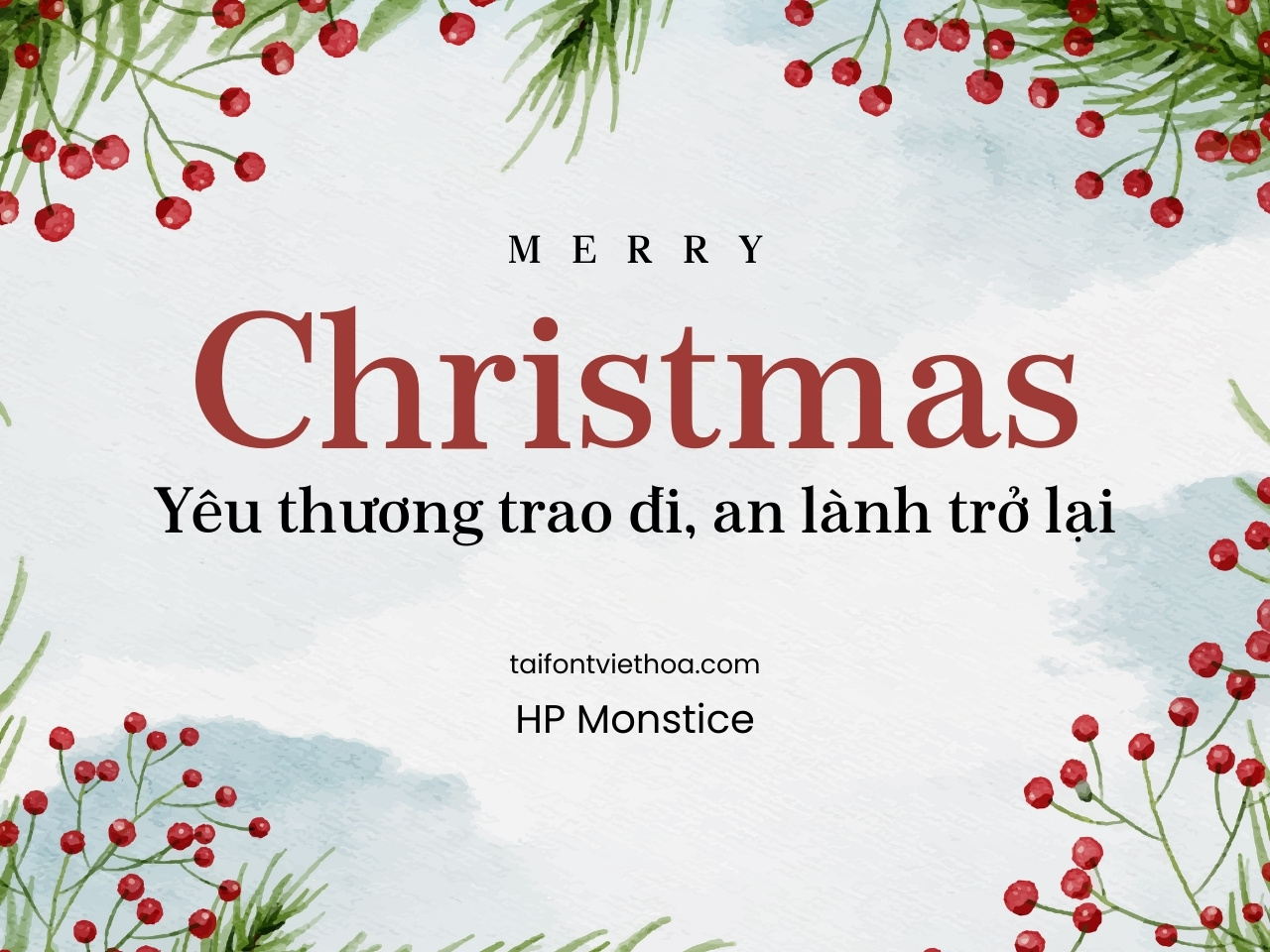
Giới thiệu font Hp Monstice – Bộ font serif trang trí ấn tượng từ Seventhimperium
Hp Monstice là bộ font serif trang trí đặc sắc được thiết kế bởi Seventhimperium – một nhà thiết kế nổi tiếng với các kiểu chữ mang tính biểu cảm cao, thích hợp cho những thiết kế đậm chất lễ hội, hoài cổ và độc đáo. Font kết hợp giữa phong cách serif cổ điển với những đường nét trang trí hiện đại, mang đến cảm giác vừa sang trọng, vừa nghệ thuật. Phiên bản Việt hóa trọn bộ được thực hiện bởi Mộc Hạ, hỗ trợ đầy đủ tiếng Việt và hơn 90 ngôn ngữ khác, đảm bảo khả năng sử dụng rộng rãi cho cộng đồng thiết kế trong nước. Font đã được taifontviethoa.com chọn lọc kỹ lưỡng, sưu tầm và chia sẻ đến người dùng như một lựa chọn đậm chất cảm xúc, thích hợp cho các dịp lễ hội hoặc dự án cần nhấn mạnh yếu tố thẩm mỹ và truyền thống.
Đặc trưng thiết kế nghệ thuật và ứng dụng của Hp Monstice
Hp Monstice sở hữu cấu trúc chữ đậm, thanh đậm rõ nét và nhiều chi tiết được cách điệu tinh tế như nét cong uốn lượn, chân chữ vát gọn hoặc đuôi kéo dài nhẹ nhàng – tạo nên tổng thể font mềm mại, cao cấp và dễ gây ấn tượng. Với phong cách rõ ràng và tính nghệ thuật cao, bộ font này phù hợp cho thiết kế poster Giáng sinh, bìa sách cổ điển, bao bì ẩm thực, thương hiệu thực phẩm handmade, logo quán cafe, cũng như các ấn phẩm truyền thông mùa lễ hội. Đặc biệt phù hợp với các ngành như ẩm thực, bất động sản mang phong cách hoài cổ, spa, giáo dục nghệ thuật, ảnh cưới và các sự kiện như Tết, Giáng sinh, lễ kỷ niệm hay ra mắt thương hiệu mới.